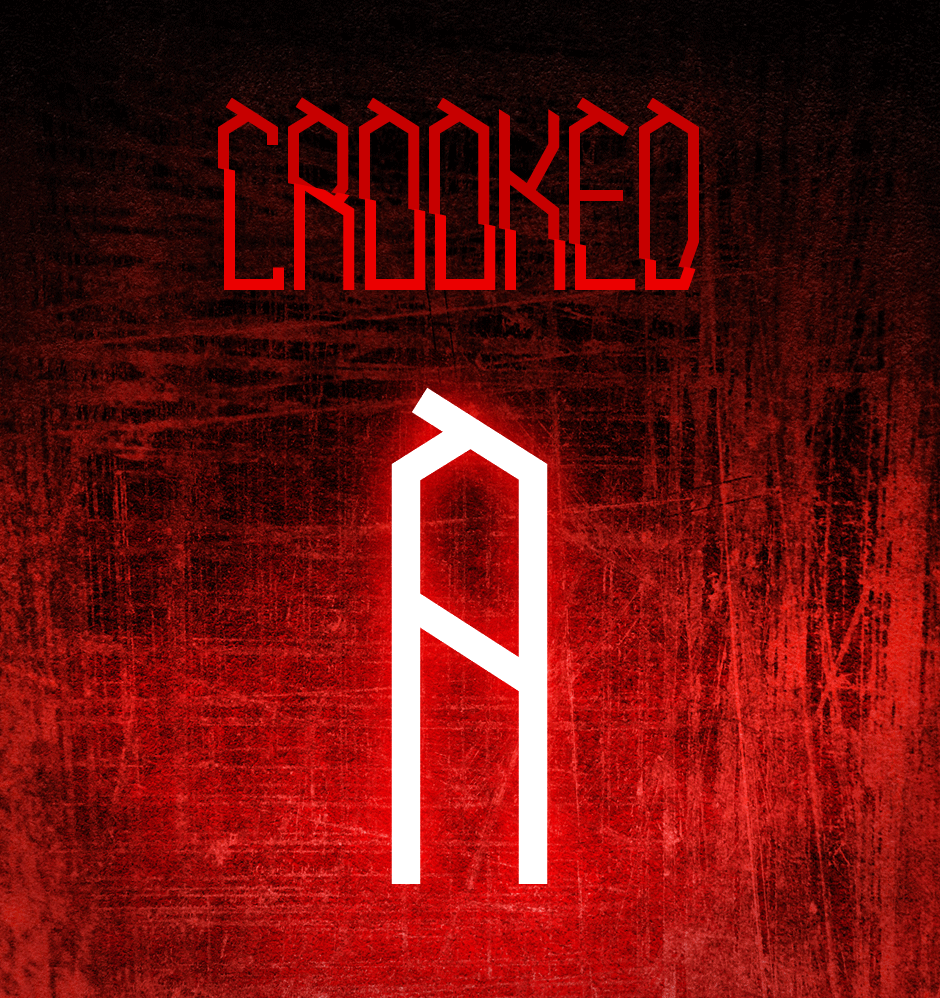
CROOKED체
그린에그블로그에서 배포하는 영문폰트 CROOKED체입니다. 제작자의 설명으로는 거칠고 강렬함이 느껴지는 폰트로CROOKED는 ‘삐딱하게’라는 뜻입니다. 가수 G-DRAGON의 ‘삐딱하게’라는 곡명에서 가져왔습니다. 사선 형태의 알파벳 모양을 본뜬 이름 입니다. CROOKED는 부정직한, 짜증나는, 비뚤어진등의 매우 부정적인 뜻을 가지고 있습니다. CROOKED한 현시대를 비꼬는 표현입니다. 그렇다고 꼭 부정적인 표현만 있는 건 아닙니다. 한 번쯤 세상을 비뚤어진 시선으로 보자는 의미도 있습니다. 남들과 다른 비뚤어진 시선에서 좋은 아이디어가 나올 수 있지 않을까요?^^
CROOKED체의 모양을 살펴보세요. 세로로장체인 글자모양에 삐침이 있는 매력적인 모습입니다. 로고나 타이틀로도 손색없는 폰트입니다.